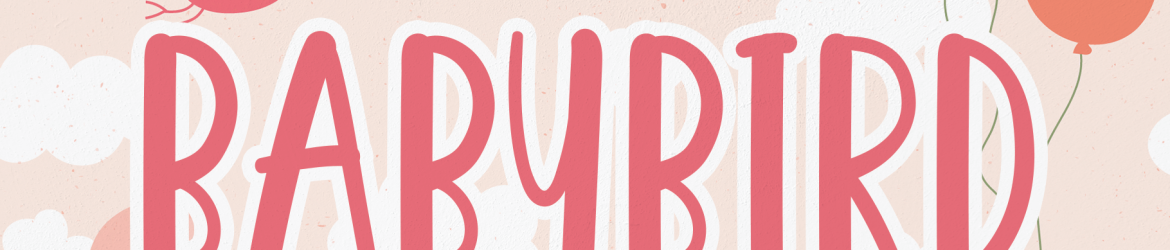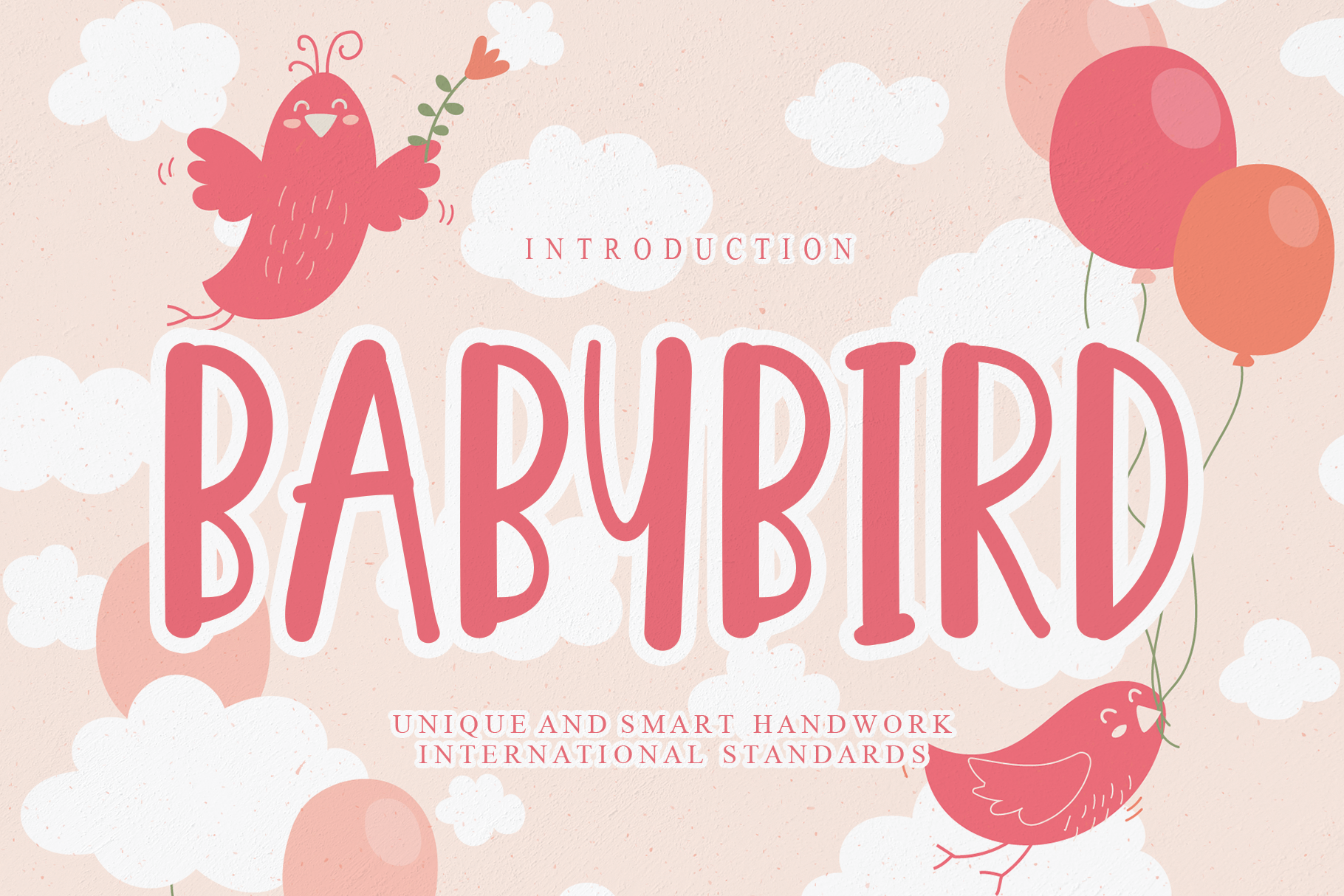
Babybird Font – Fonte Grátis
Babybird Font
A fonte Babybird é uma escolha perfeita para quem procura um visual alegre e desafiador para seus projetos de design. Com seu ar desenhado como uma criança quebrando regras com criatividade, essa fonte é ideal para criar designs memoráveis e enriquecedores. A designer andikastudio criou esta fonte em um estilo chamado display fonts – os tipos de texto grande e destacados utilizados geralmente nas capas de livros e revistas. Suas curvas leves e seus traços encantadores tornam a Babybird uma escolha perfeita para qualquer projeto que deseje se destacar, seja em uma apresentação ou na criação de um poster. Nada como o charme de uma criança brincando e criando coisas novas. Essa fonte é a prova disso, com seu design único e sua função multifacetada de tornar qualquer conceito mais realista e visível. Tudo isso num pacote que se encaixa tão bem em diversos tipos de projetos gráficos – da web até impressão, Babybird está pronto para ajudá-lo a criar seus designs mais inspiradores. Seja você um designer gráfico ou uma pessoa criativa em busca de novas maneiras de expressar seu pensamento visualmente, Babybird pode ser o que você precisa. Escolha-a e permita-se ser a criança quebrando regras por dentro da sua criação!